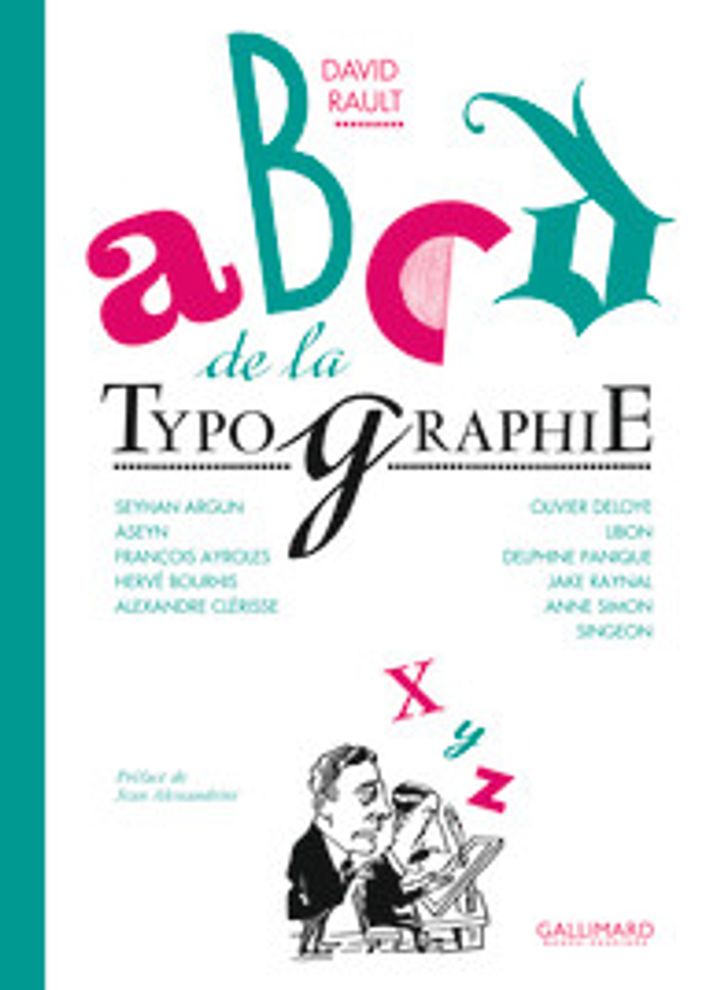
ABCD de la typographie
Le synopsis de l'album ABCD de la typographie
Quel rapport y a-t-il entre notre lettre A et un bœuf ? Pourquoi une affiche composée en Comic Sans paraîtra moins sérieuse qu'une autre composée en Trajan ? D'où vient la typographie et quels artistes ont marqué son histoire ?
Omniprésente dans les livres, dans les publicités et sur les écrans, la typographie reste un art méconnu. Onze dessinateurs racontent ici de manière accessible et ludique les grandes étapes historiques de sa création, de la naissance de l'écriture occidentale à la photocomposition, en passant par la Rome antique, le Bahaus et la classification Vox.
David Rault, graphiste et spécialiste de la typographie, s'entoure de 11 illustrateurs pour confectionner un ouvrage passionnant retraçant l'histoire de la typographie latine, des prémices de l'écriture jusqu'à nos jours. Enfin un livre abordable sur ce sujet, destinés aux amateurs et autres curieux.
La typographie est partout dans notre vie : livres, affiches, signalétiques, logo... Elle est le support principal du mode de communication de notre monde occidental. Son design lui-même est porteur de sens. En se focalisant sur onze étapes clés de son histoire, l'auteur retrace l'aventure de la typographie latine, de l'écriture et de la communication visuelle occidentale.
L'auteur revient sur cet incroyable outil de communication, nous expliquant les formes des lettres et des polices ainsi que le mystère de leurs noms, nous expliquant au passage pourquoi la Comic Sans paraît bien moins sérieuse que la Trajan. Chaque chapitre met en lumière un ou plusieurs personnages ou procédés qui ont marqué l'histoire de la typographie. Les chapitres sont courts, concis et clairs. Remplie d'informations et d'anecdotes, la lecture est passionnante et abordable pour un public de novices.
Chaque chapitre est illustré par un dessinateur différent. Cette absence d'homogénéité stylistique dynamise l'ouvrage, nous plongeant dans un univers différent à chaque étape clé abordée. La plupart des dessinateurs se sont amusés à reproduire manuellement les formes des lettres, de manière approximative, plutôt que de se tourner vers les outils informatiques. Il y un véritable jeu de mise en abîme, exercice de style où chacun joue avec la typographie pour parler de la typographie. Comme le fait également Jean-Christophe Menu qui réalise la très belle conception graphique de cet ouvrage.
L'ABCD de la typographie est un bel objet, bien conçu et passionnant. Le format bande dessinée est un format original et innovant pour nous faire découvrir ce domaine. Un livre à mettre entre toutes les mains des amoureux des mots, des lettres et de l'écriture.